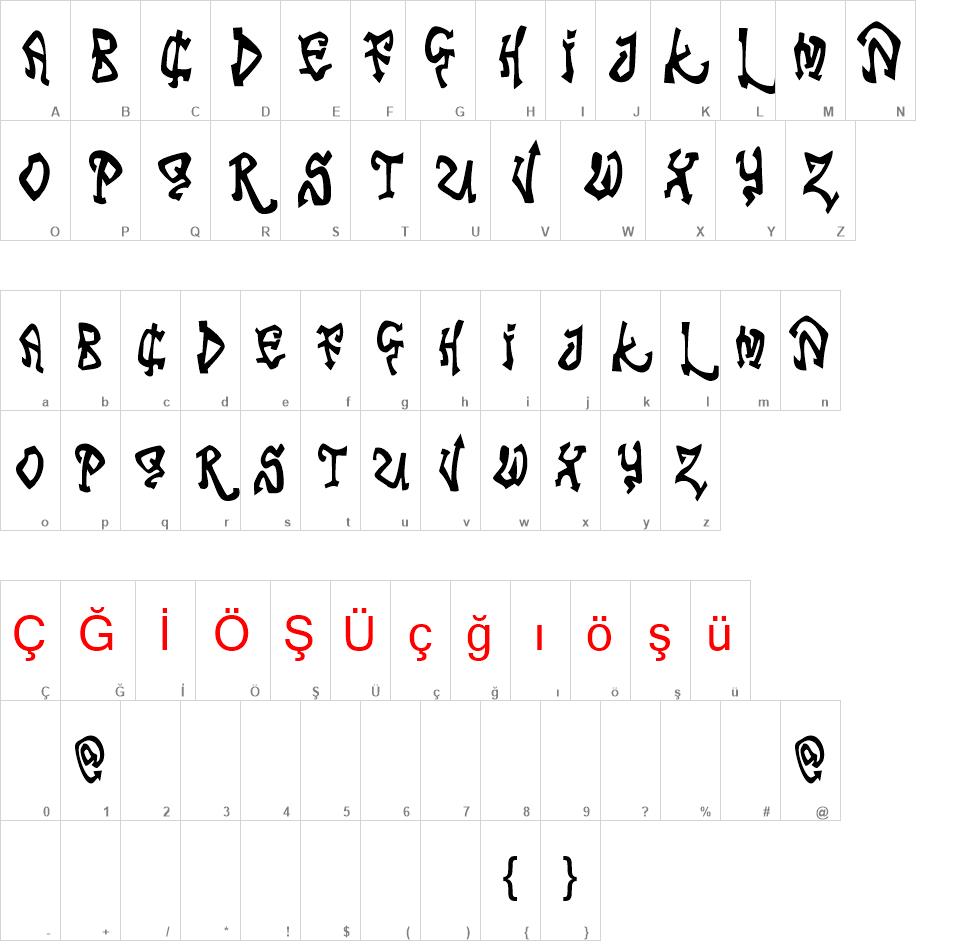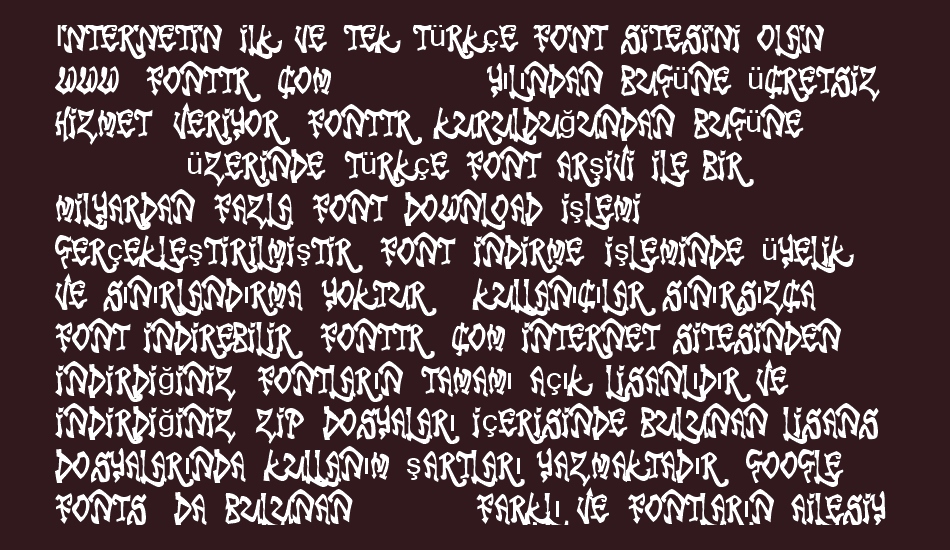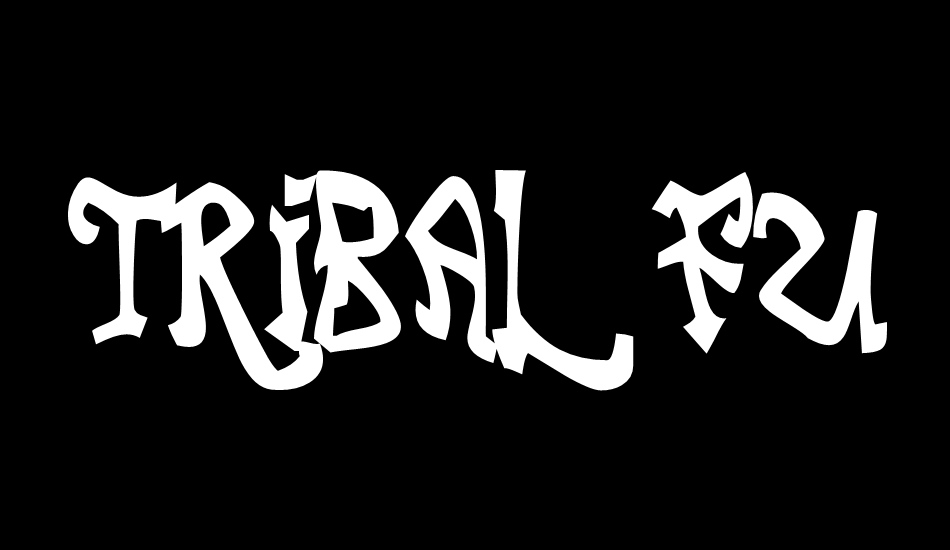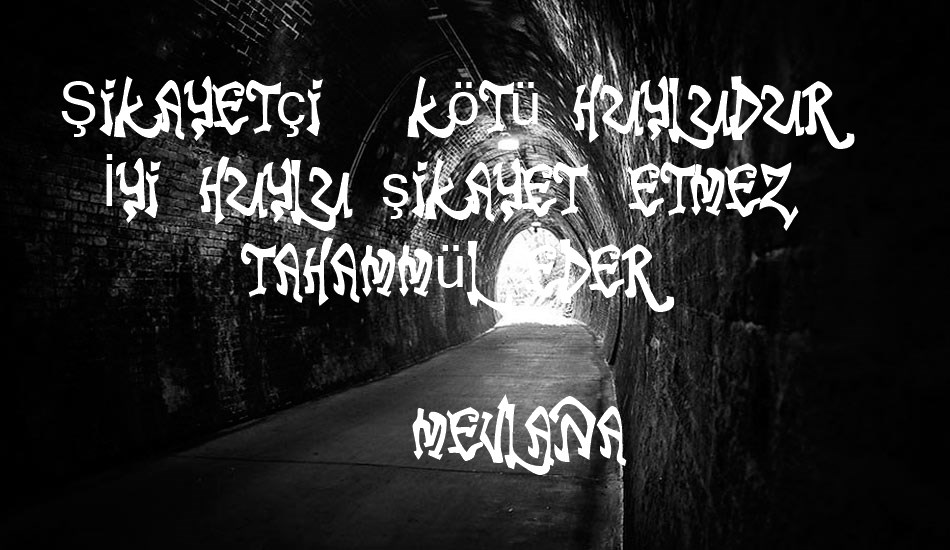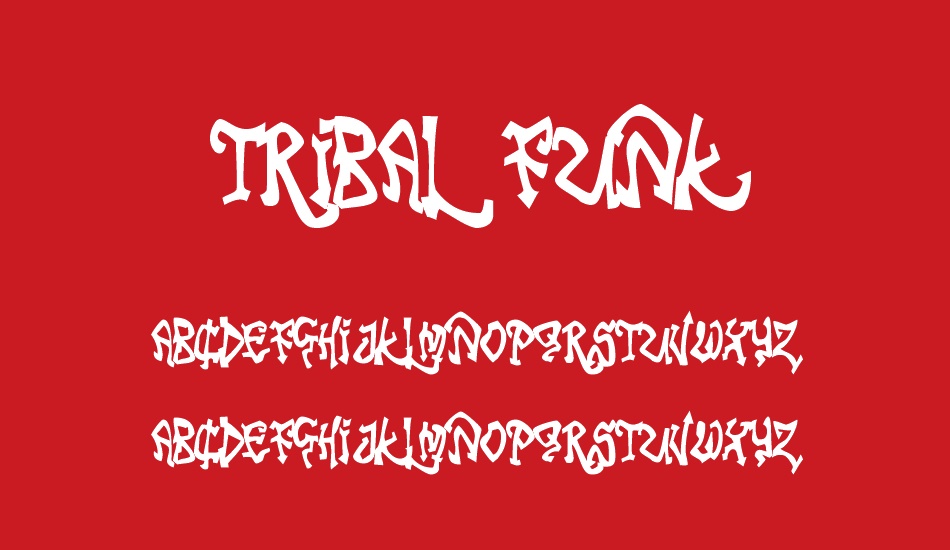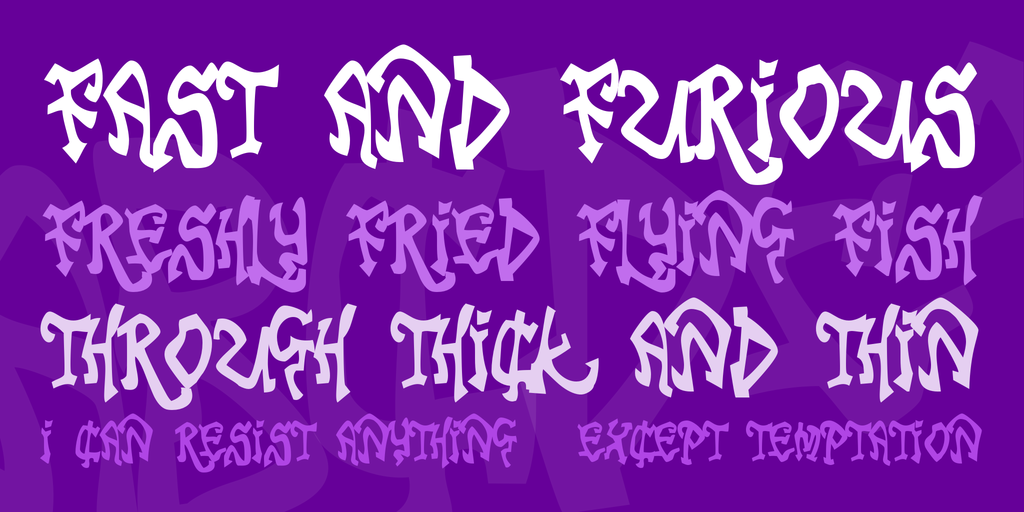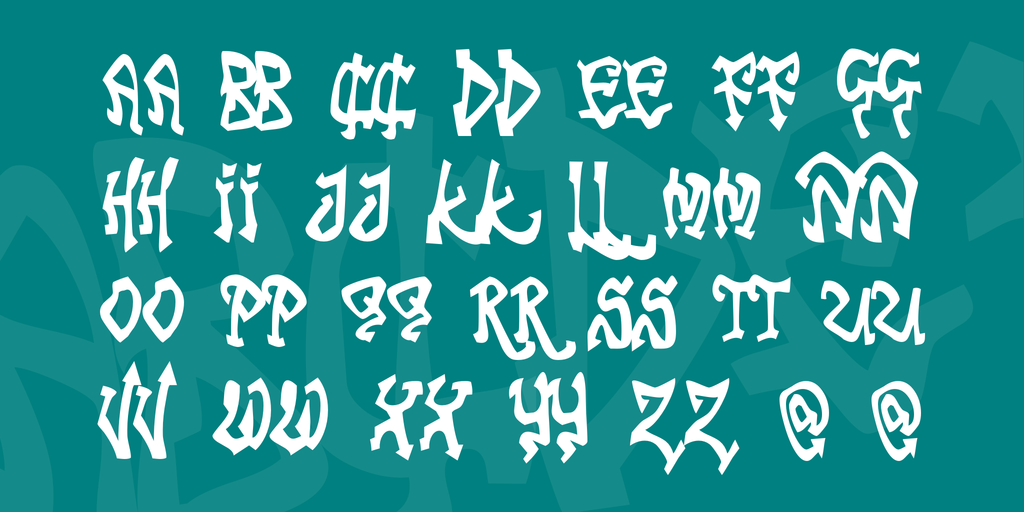
Tribal Funk font
Tribal Funk
Tribal Funk ist eine Graffiti-Schrift. Es hat eine afrikanische Atmosphäre, aber mit einem modernen Rand. Benannt von Todd Maroney, in einem Wettbewerb.